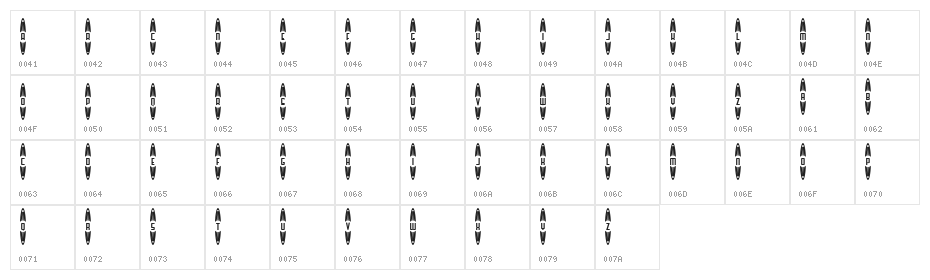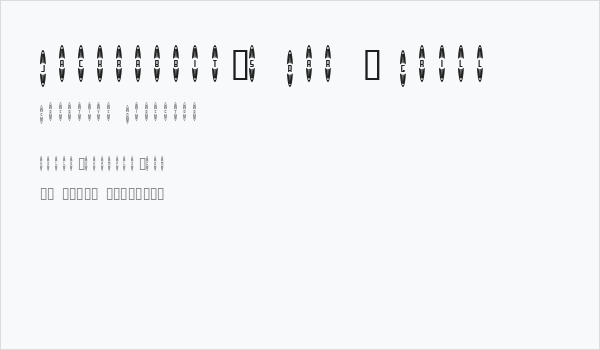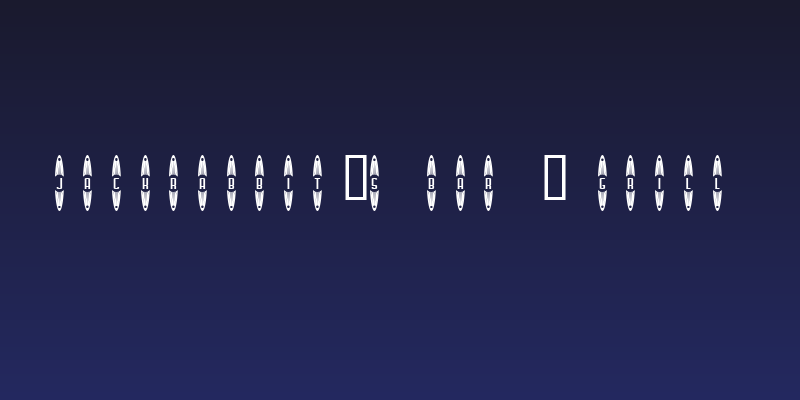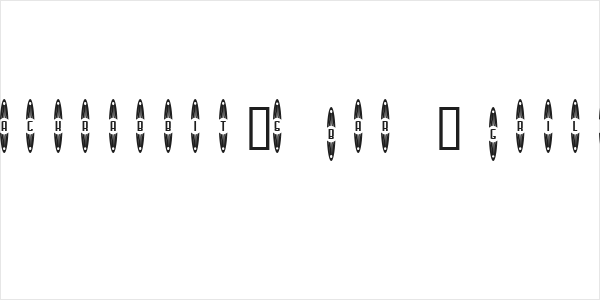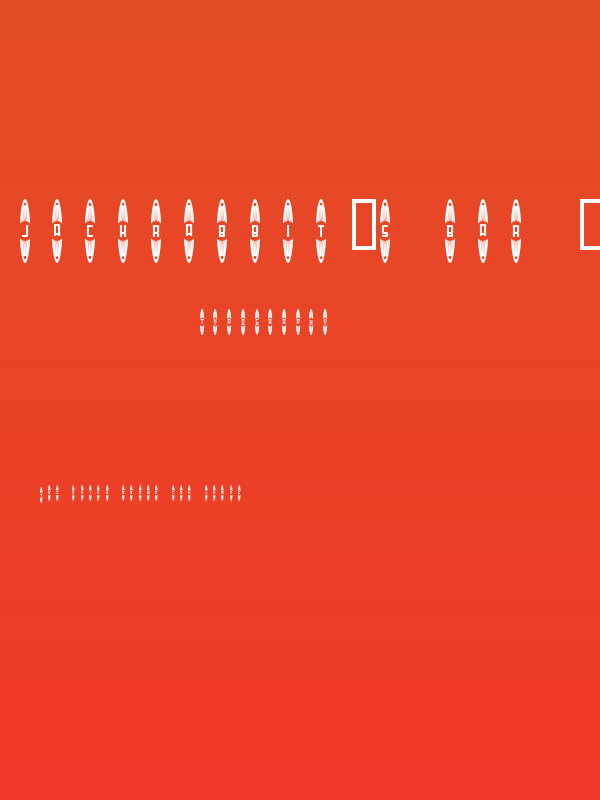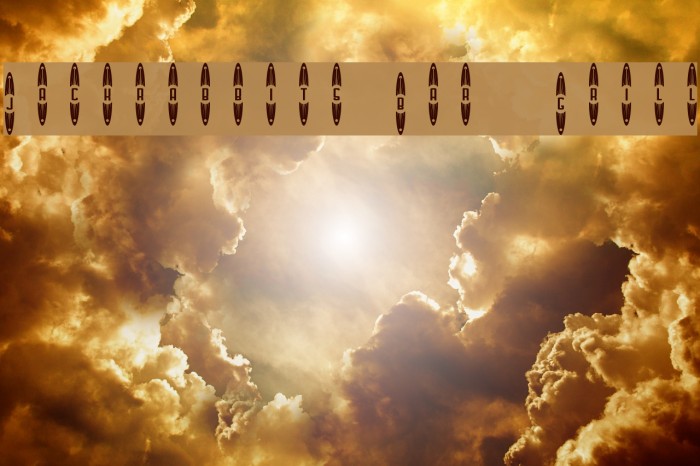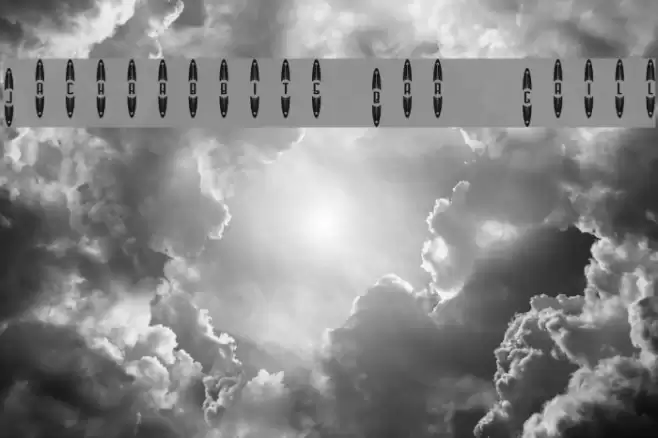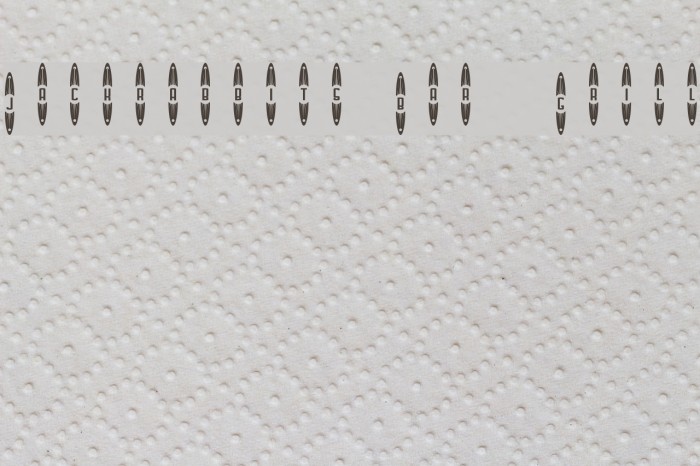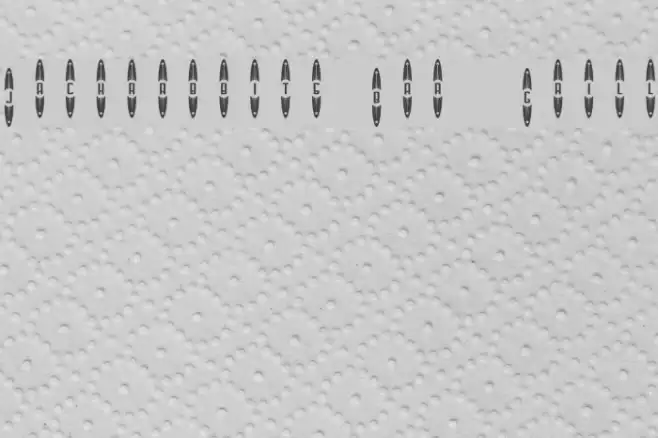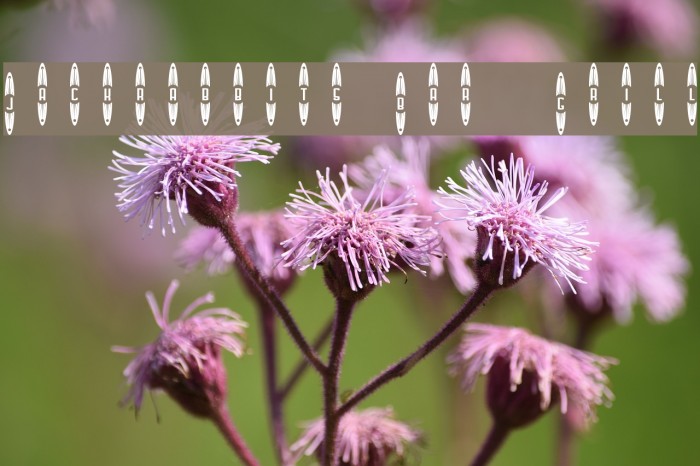
Jackrabbit's Bar & Grill Font
| Nombre | Jackrabbit's Bar & Grill |
| Caso de uso | Logos, Headlines, Posters |
| Proyectos propuestos | Ideal for surf shops, beach-themed events, casual branding, and playful designs. |